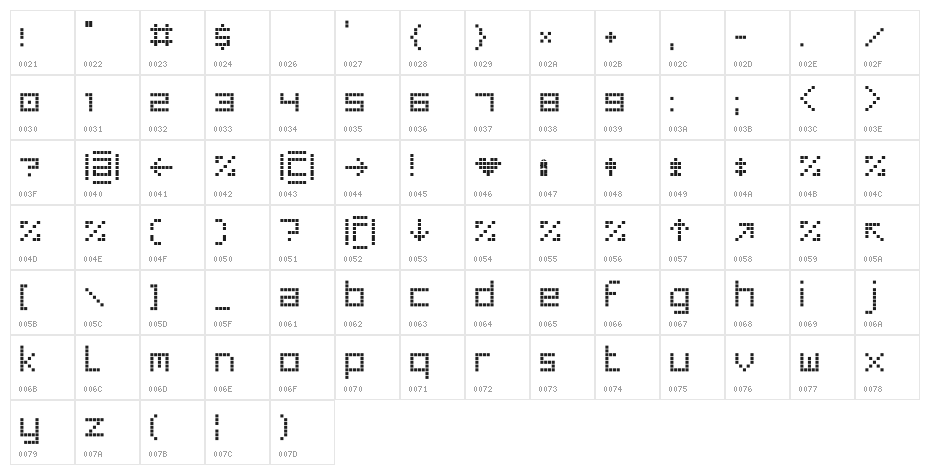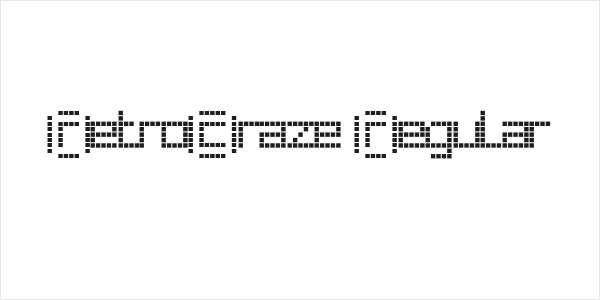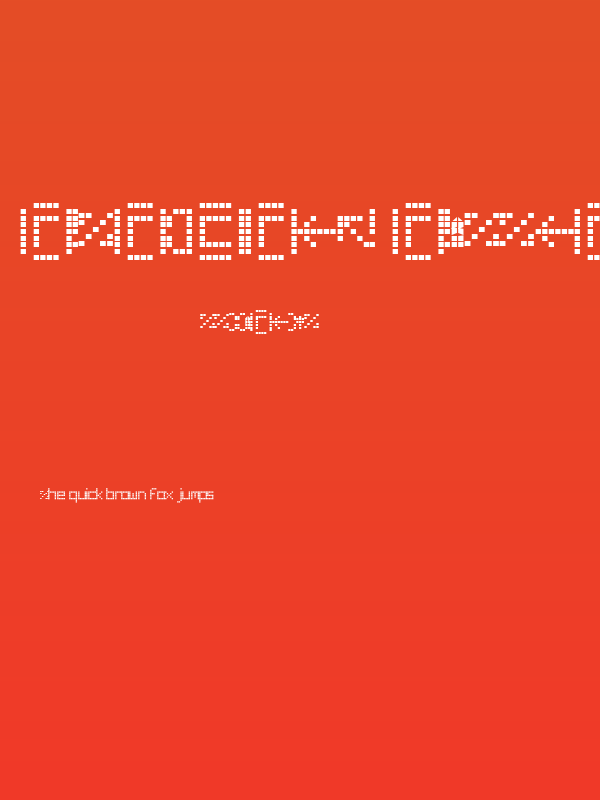
RetroCraze Regular Font
✎ Pixel
| Progetti proposti | Ideal for projects that aim to capture a retro or nostalgic feel, such as video game graphics, digital art, posters, and themed event invitations. |